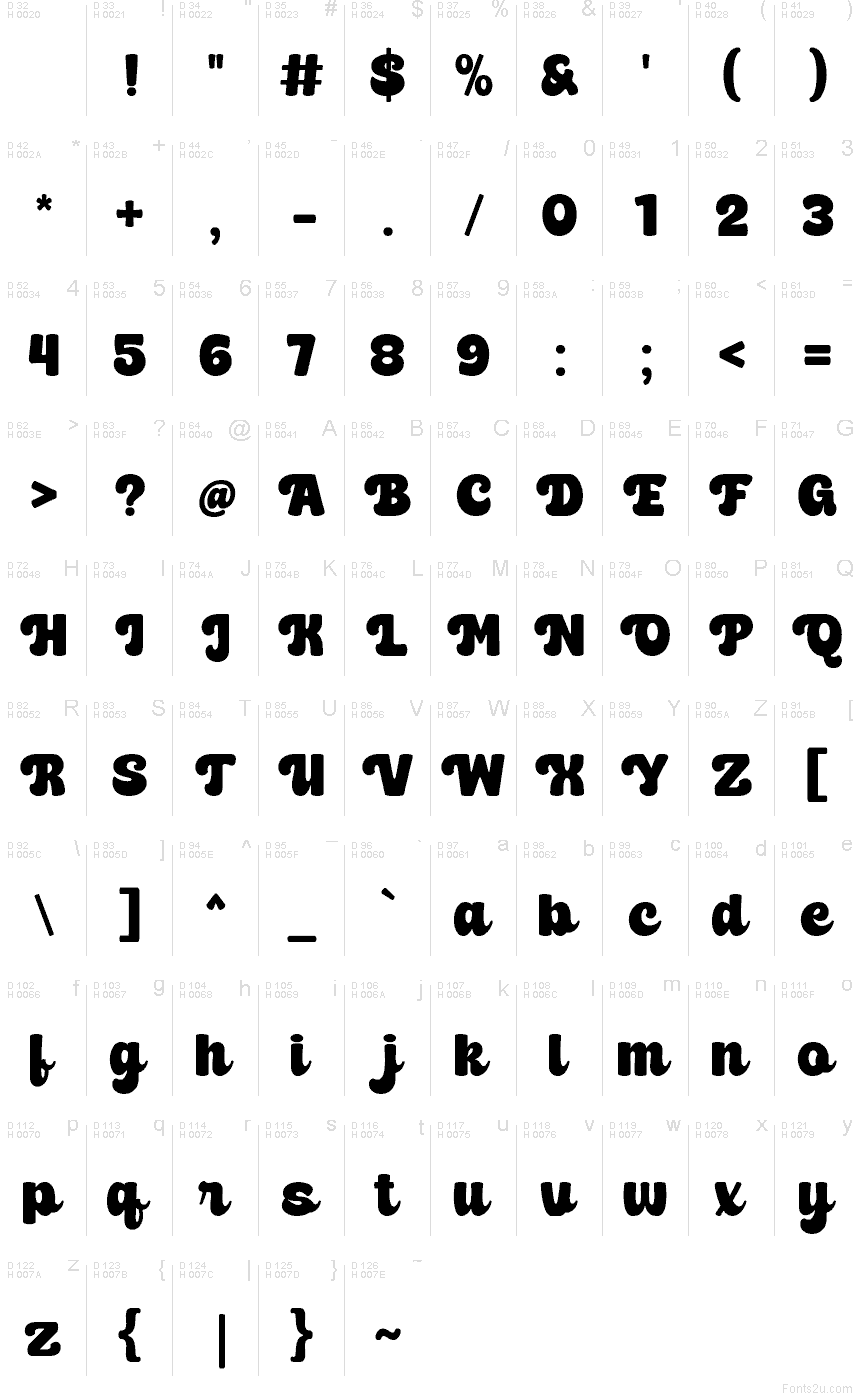
Milky Bun od Burhan Afif to darmowy, retro font displayowy o miękkim, przytulnym klimacie, przypominającym wystawę cukierni. Litery są grube i pękate, z zaokrąglonymi łączeniami, obłymi kształtami i żywym rytmem, co sprawia, że cały krój jest bardziej słodki niż techniczny.
Sprawdzi się idealnie w brandingu kawiarni, opakowaniach deserów, nagłówkach plakatów, okładkach książek dla dzieci oraz radosnych grafikach social media, gdzie potrzebujesz wyrazistych liter z przyjaznym stylem retro. Jako darmowy font, świetnie nada się także do krótkich tytułów, logotypów w stylu naklejek i chwytliwych nazw produktów, ponieważ te miękkie kształty przyciągają wzrok i nadają nawet kilku słowom przytulny, nostalgiczny klimat.